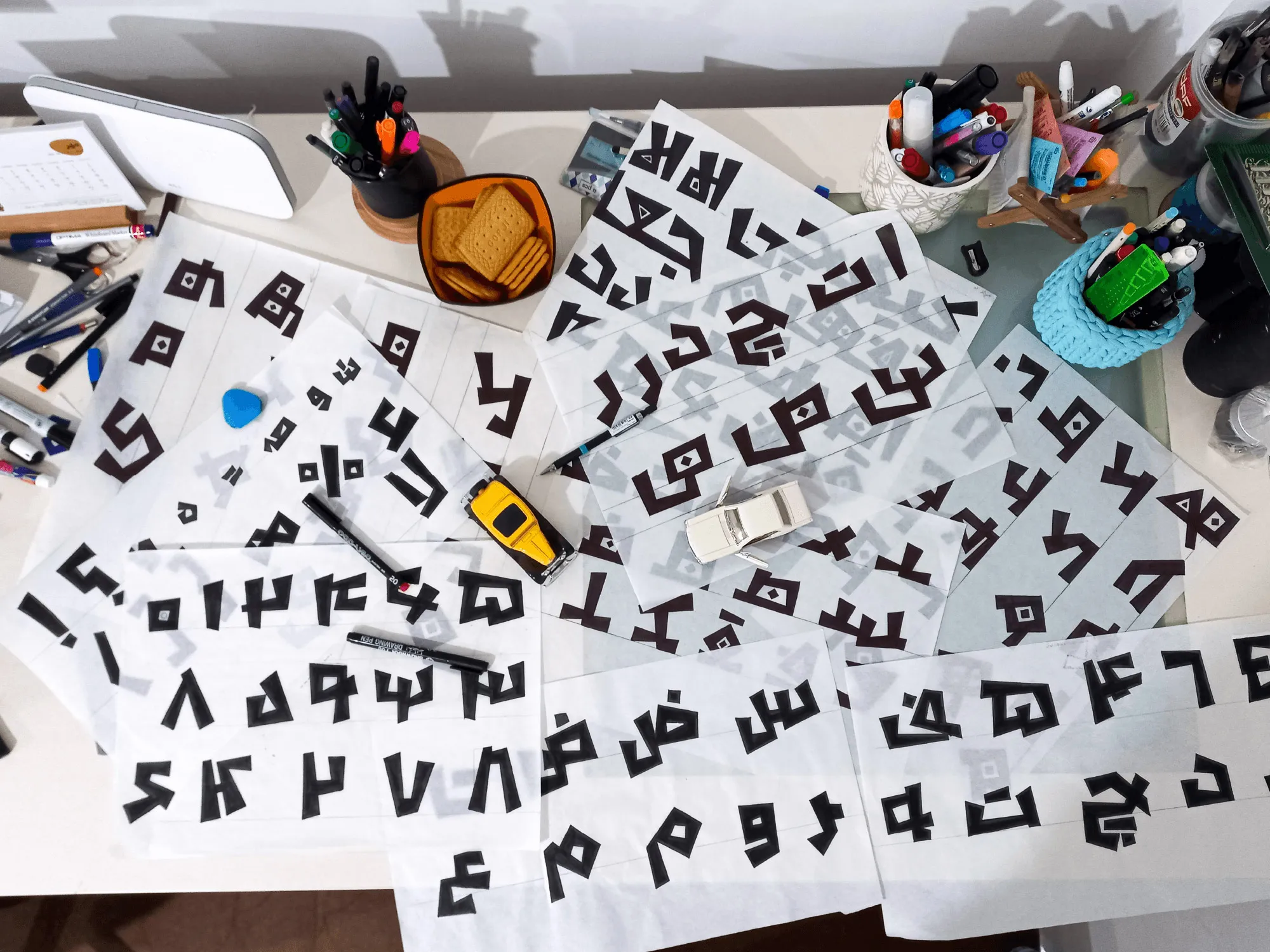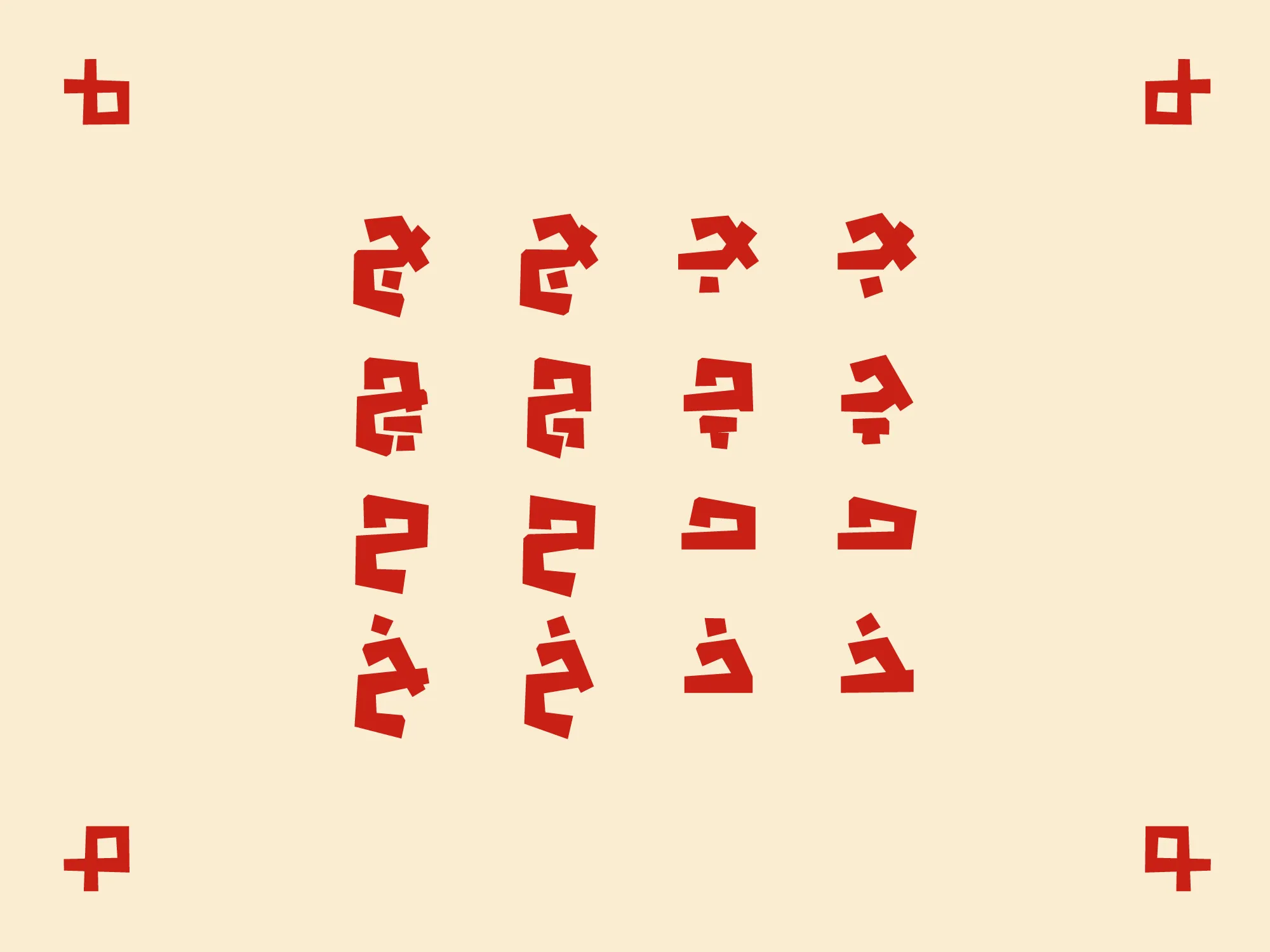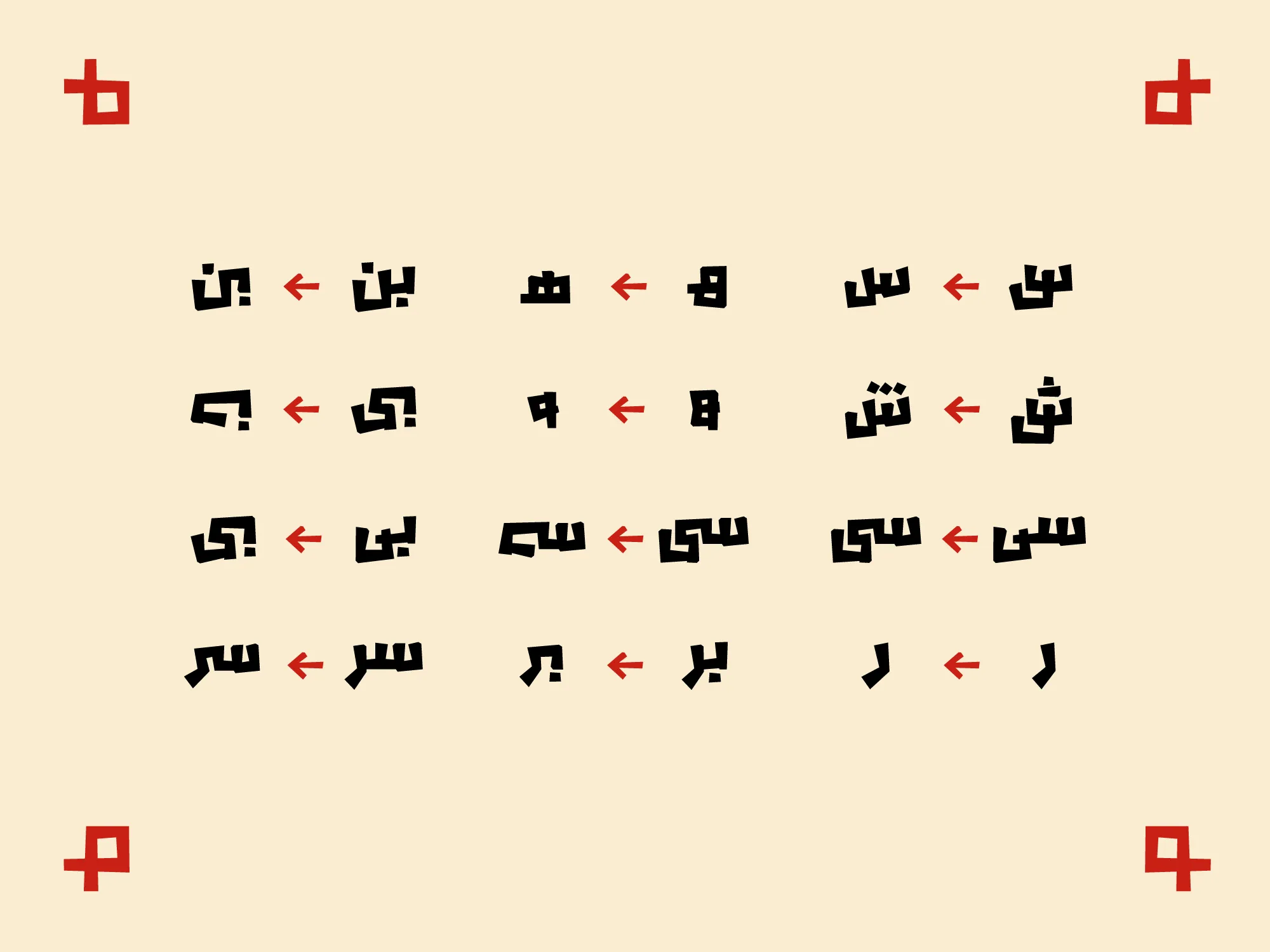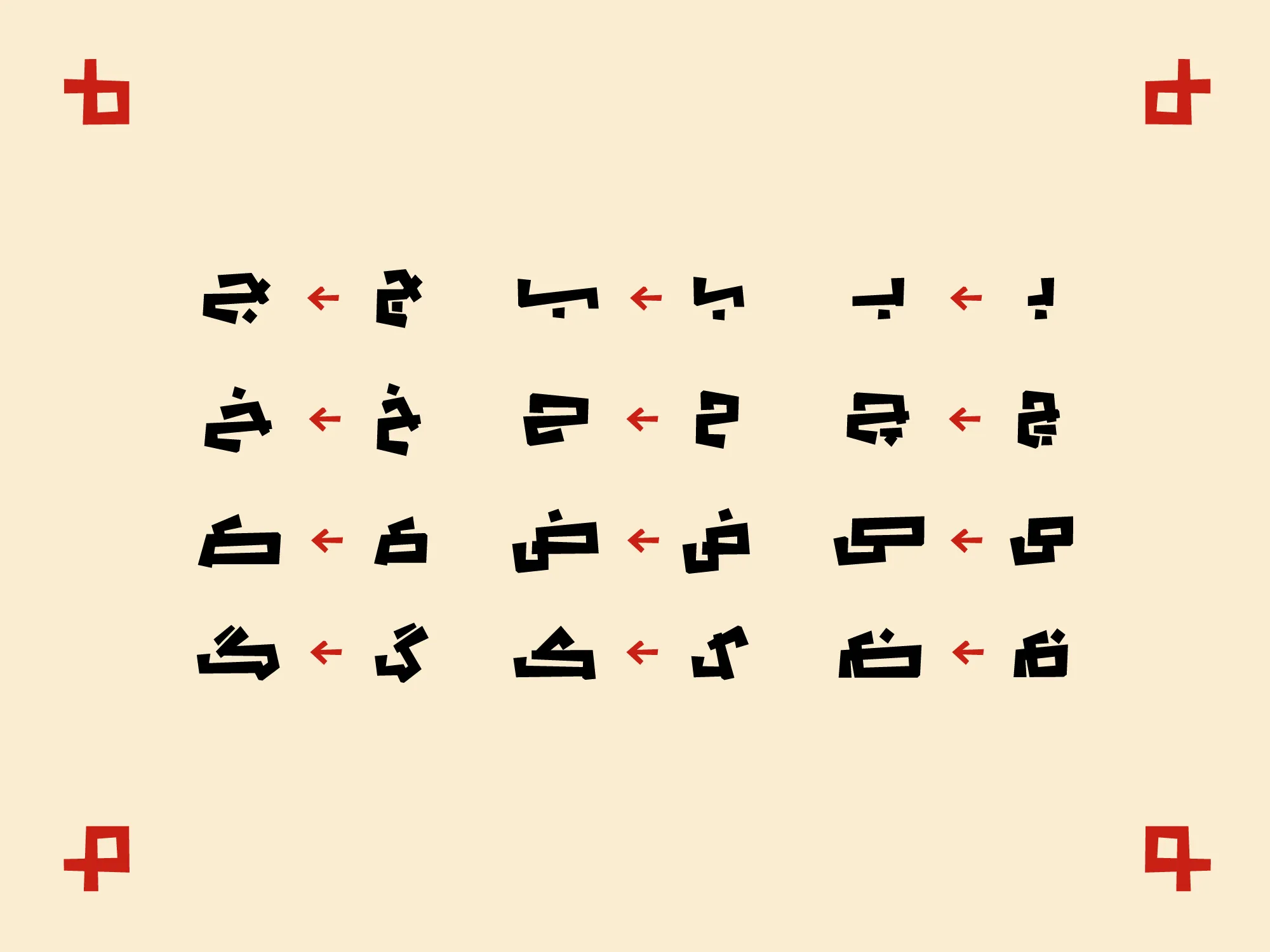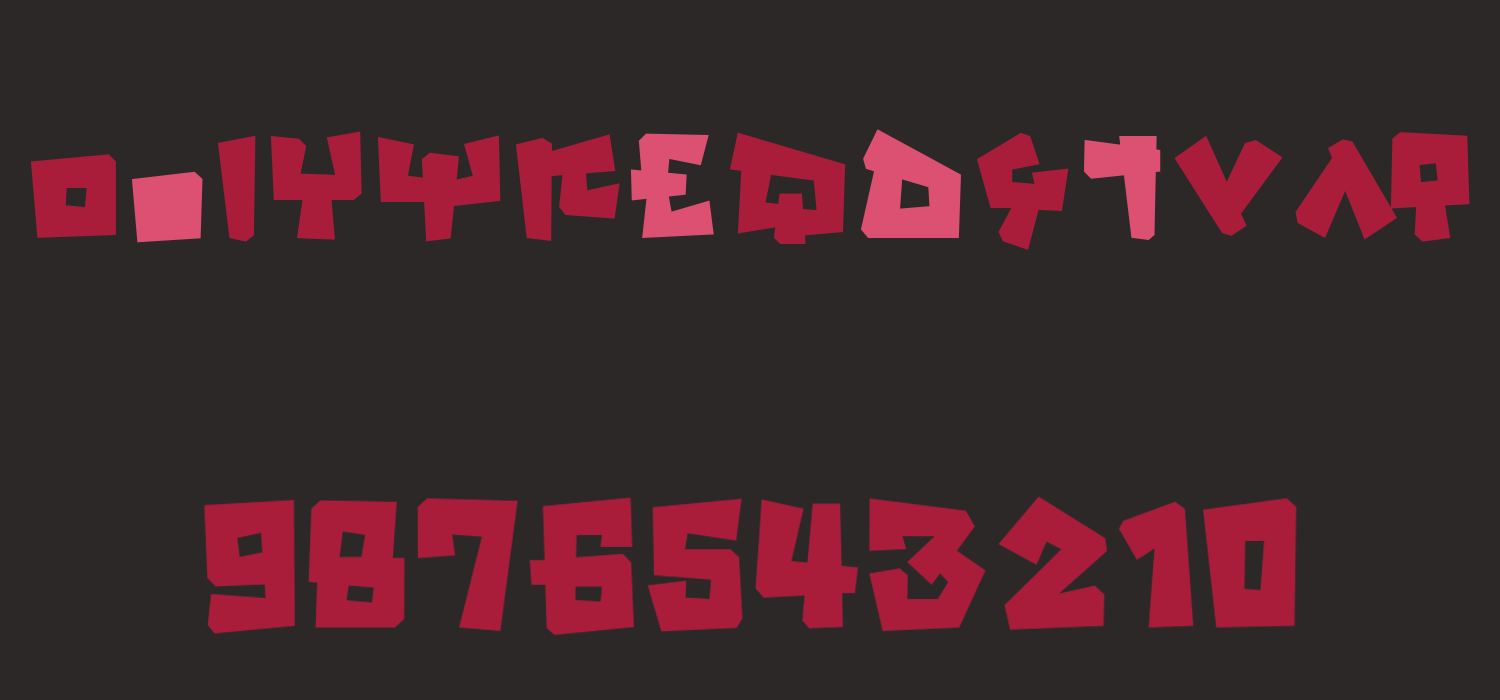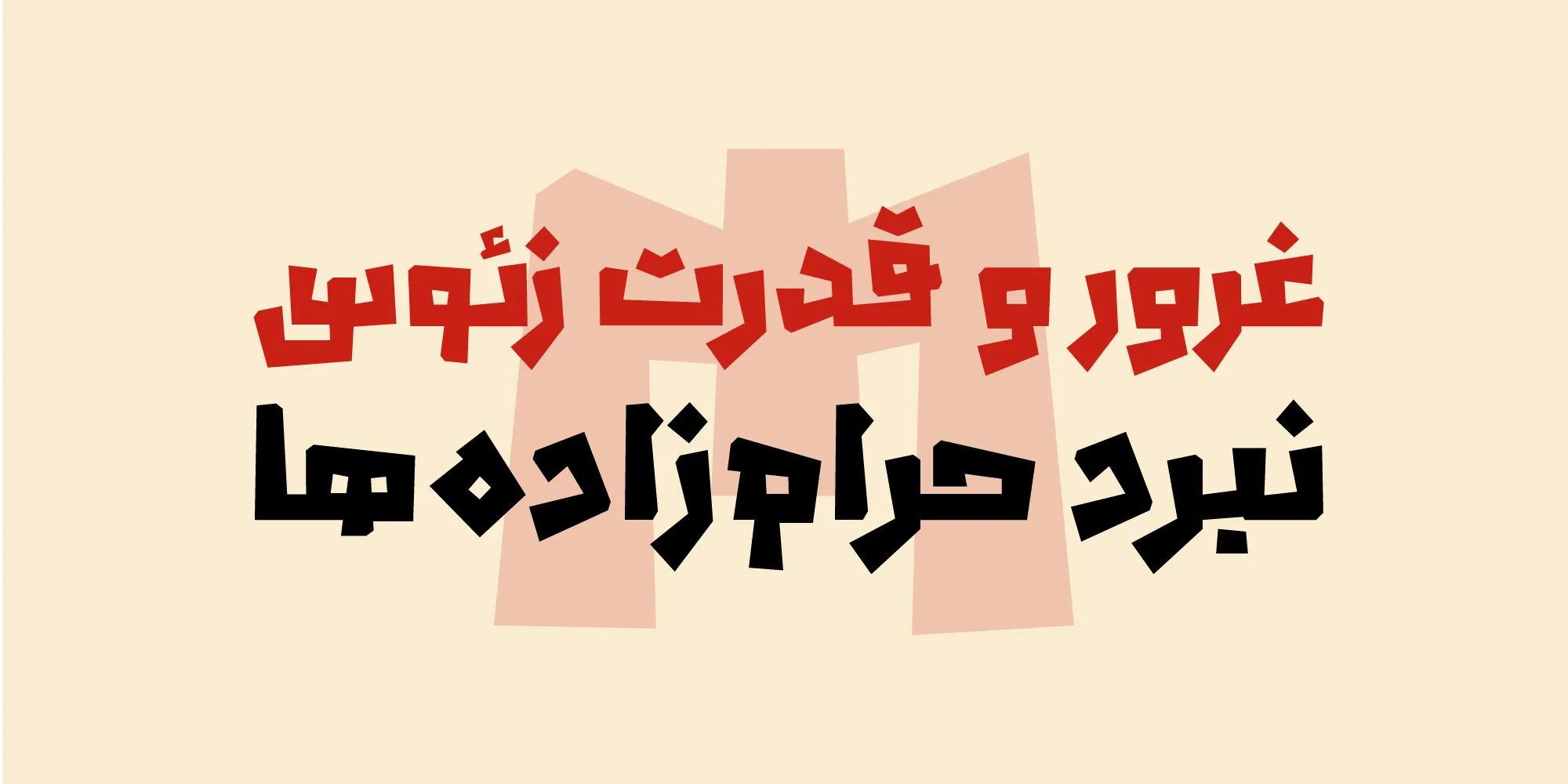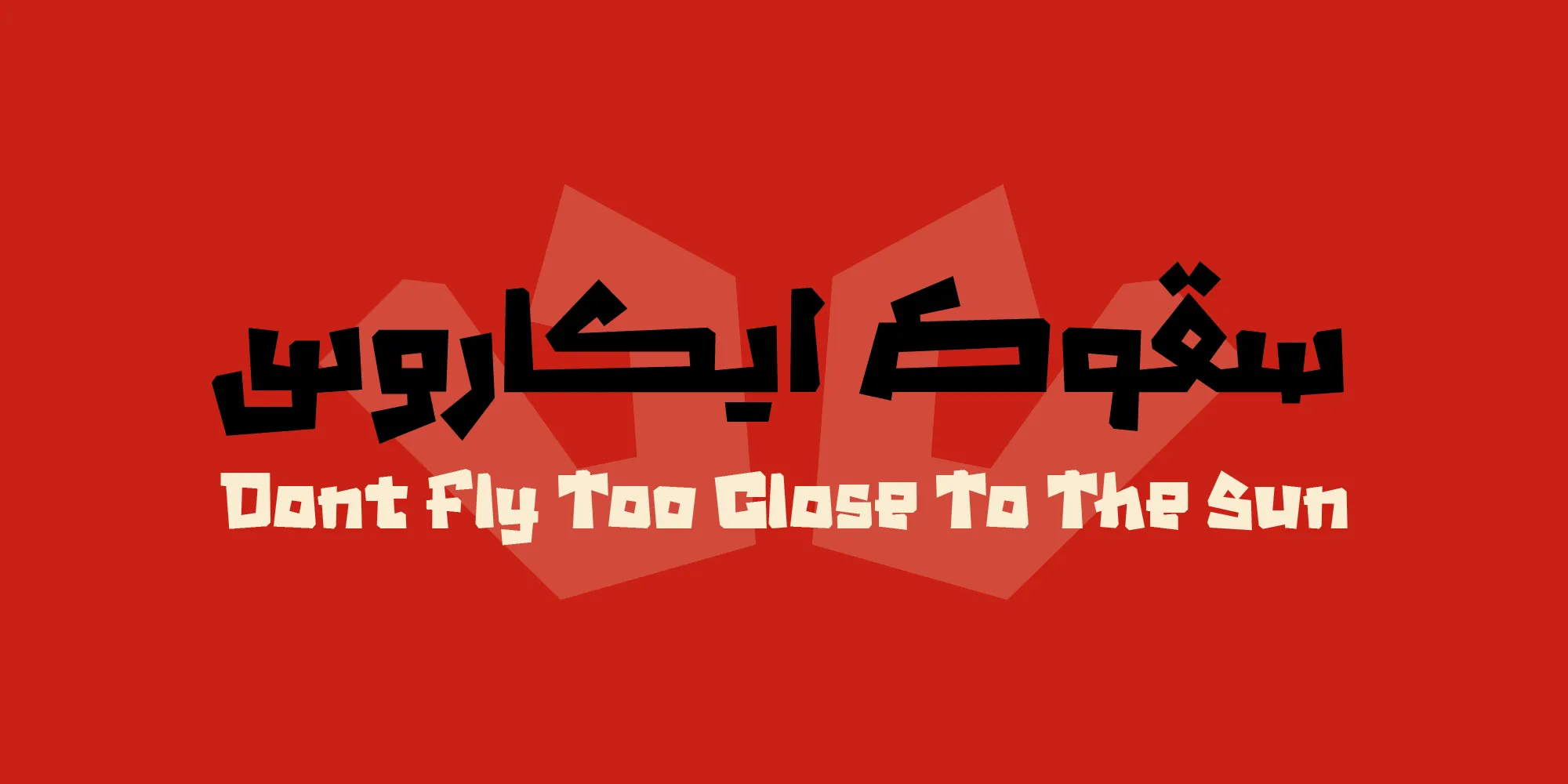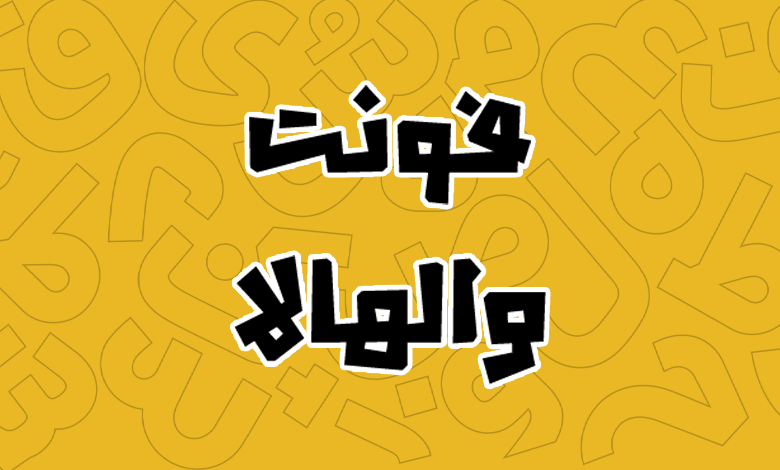
فونت والهالا (Valhalla)
فونت والهالا (به انگلیسی: Valhalla) قلمی با ساختاری کاملا متفاوت است که با الهام از دنیای اساطیر اسکاندیناوی طراحی شده است. این قلم شخصیتی جدی، خشن و بیکله دارد که رفتاری مشابه یک وایکینگ را در ذهن مخاطبان دارد. فونت والهالا رایگان نیست و در یک وزن قابل خریداری است.
طراحی فونت Valhalla توسط امیرحسین رئوف صورت گرفته که جزو اولین پروژههای این طراح تایپ است. وی با اینکه در ابتدای مسیر طراحی تایپ است، اما با پروژهای قوی فعالیت خود را در این زمینه آغاز کرده که حرفها برای گفتن دارد. احتمالا شما هم با دیدن این قلم به یاد انیمیشن جذاب ویکی خواهید افتاد.
در ادامه این نوشته از سایت فونتچی به معرفی، بررسی و دانلود فونت والهالا خواهیم پرداخت؛ قلمی که با شخصیت جنگجو، بی ثبات و کلهشق خود حسابی میتواند در حوزههای مختلف سرو صدا بهپا کند.
بررسی و دانلود فونت والهالا (Valhalla)
در فونت والهالا شاهد شکستگی و تیزیهای متعددی در فرم حروف هستیم که در بین فونتهای فارسی بینظیر است؛ گویی آنها سربازانی همیشه مسلح و آمادهی نبرد هستند!
این شکستگیها از قاعده و قانون خاصی پشتیبانی نمیکند و رفتاری کاملا اختیاری از خود دارند. خبری هم از زوایا و منحنیها در این قلم نبوده و ساختار چنین بخشهایی در خطوط قائم و افقی کاملا ناگهانی است.
سبک طراحی و وزن فونت والهالا
در طراحی فونت والهالا فقط از خطوط صاف و بدون انحنا استفاده شده است. هدف از این شکستگیها، تیزیها، فرمهای ابتدایی و عجیب و غریب، القای حس باستانی و رمزآلود دنیای اساطیری اسکاندیناوی است.
ایدهی طراحی فونت والهالا از علاقهی من به دنیای اساطیر اسکاندیناوی شروع شد. والهالا روحیهی باستانی و بدوی دارد و از کتیبههای اسکاندیناوی استخراج شده است.
ویژگیهای حروف روی کتیبهها این ایده را به من داد تا حروف را در عین یکپارچگی متفاوت و گاها بینظم طراحی کنم؛ هیچ حرفی شبیه به دیگری طراحی نشود! انگار که من هم بهدلیل محدودیتهایی نتوانستم حروف را دقیقا مثل هم طراحی کنم.
متفاوت بودن همهی حروف بایکدیگر، رفتارهای تصادفی و از همه مهمتر تبدیل کردن چنین ویژگیهایی به یک فونت اصلی ترین چالش من در طراحی والهالا بود.
امیرحسین رئوف؛ طراح فونت والهالا.
ساختار طراحی این قلم حتی در حروف یکسان نیز کاملا متفاوت است. همانطور که در تصویر زیر میبینید، حروفی همچون «ج، چ، ح، خ، د، ذ، ر، ز، ژ، س، ش و…» که ظاهری یکسان داشته و صرفا از نظر نقطهگذاری متفاوت هستند، اما ظاهری کاملا متفاوت را در بخشهای مختلف کلمات از خود نشان میدهند.
از سوی دیگر این ساختار متفاوت در نقاط نیز پیادهسازی شده است. طوریکه مانند تصویر زیر شاهد استفاده از چندین مدل مختلف از نقطهگذاری چسبان هستیم. برخی دارای زاویه بوده و ساختاری تیز دارند، برخی دیگر نیز بهصورت خطی و ادغام شده در یکدیگر هستند.
این قلم در وزن Black عرضه شده که دارای ظاهری نسبتا چاق است و میتواند برای استفاده در عناوین مورد استفاده قرار گیرد. ساختار قلم کاملا هندسی است و از قانون خاصی برای چیدمان حروف مختلف تبعیت نمیکند.
پشتیبانی از ۵ زبان متنوع
فونت والهالا چندمنظوره است و از چندین زبان مختلف به لطف رسمخط فارسی با تاریخچهای کهن پشتیبانی میکند. جدای از زبان فارسی شاهد استفاده از این قلم برای سایر زبانهای خاورمیانهای هستیم.
شکل حروف در تمامی زبانها یکسان است و تنها حروفی که دارای ظاهر متفاوت نسبت به فارسی هستند، گلیف جداگانه قرار داده شده است. همچنین در حروف جایگزین میتوان گفت که از طراحی حروف در زبان اردو وام گرفته شده است.
برای زبان عربی ساختار اعراب کاملا استاندارد است و زمانی که همراه با سایر اعراب «تشدید، همزه یا تنوین» باشند، موجب بههم ریختگی نخواهد شد.
در زبان کوردی هم شاهد پشتیبانی از گلیفهای تزئینی هستیم که میتوانید به شکل استانداردی از این قلم بهره ببرید. دیگر زبان پشتیبانی شده اردو است که علاوهبر حروف استاندارد، از گلیفهای تزئینی نیز پشتیبانی کرده است.
فونت Valhalla انگلیسی نیز دارای طراحی اختصاصی بوده و بر اساس همان ساختار حروف فارسی طراحی شده است. بر خلاف سایر قلمهای هندسی و با این سبک خاص که از فونتهای لاتین دیگر الهام گرفتهاند.
از نسخه لاتین این قلم هم میتوانید در زبان انگلیسی و سایر زبانهای برپایه لاتین که حروف کاملا دارای طراحی انگلیسی هستند استفاده کنید.
دارای ترکیبات بی نظیر از حروف جایگزین
یکی از ویژگیهای قابل توجه در فونت والهالا پشتیبانی از حروف جایگزین است. بهخودی خود در این قلم شاهد سبکی هستیم که حتی حروفی با ظاهر مشترک، دارای طراحی یکسان نیستند. طراح در پیادهسازی این قلم پا را فراتر نهاده و نسخه جایگزینی هم برای بسیاری از حروف درنظر گرفته است که این فونت را بیشتر از پیش خارقالعاده میکند.
همانطور که در تصاویر زیر میبینید، میتوانید حروف و ترکیبات مختلفی مانند «س، ش، سی، ر، ه، بر، بن، بی، سر» را با ظاهری کاملا متفاوت تایپ کنید که به نمایشیتر کردن این قلم کمک میکنند. این حروف و ترکیبات محدود به موارد بالا نبوده و شامل دهها نمونه دیگر است.
اما در بحث جروف جایگزین فونت والهالا شاهد دو نسخه پیچیدهتر نیز هستیم. حالت اول با نام Low Swash کشیدهها هستند که تا حد بسیار پایین و نسبتا چشمگیری، در زوایای مختلف حروف جایگزین کشیدگی مانند تصویر زیر ایجاد شده است.
اما حالت دوم که شامل نسخهای با حد بالاتر است و با نام High Swash شناخته میشود، شاهد نسخهای با کشیدگی بسیار بیشتر که خود را بهتر نمایش میدهد هستیم.
در این نسخه کشیدگی حروف بیشتر خود را نشان میدهد که در موضوعات تبلیغاتی بهتر است از این نسخه استفاده کنید تا روی توجه بیشتر مخاطب و همچنین فاصلهگذاری بین کلمات خود را پختهتر نشان دهد.